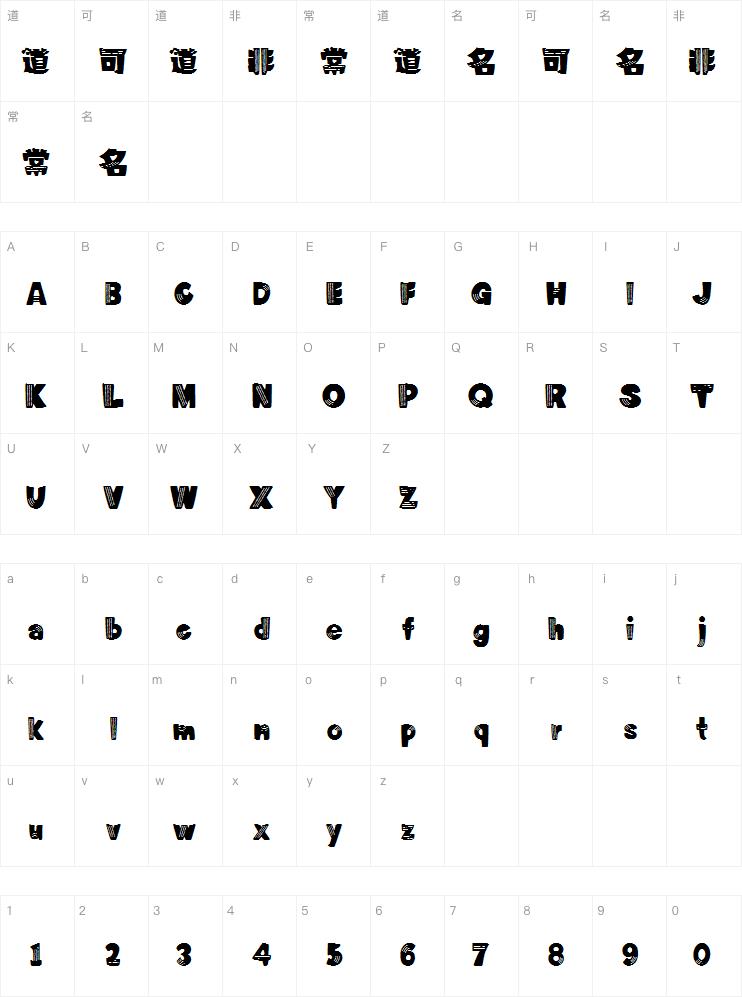
字魂上海交响乐谱体
字魂上海交响乐谱
字魂上海交响乐谱体是字魂为上海交响乐团打造的定制字体。这是一款欢快灵动仿佛可以听见声音的字形,字形笔划圆融可爱,视觉感强烈。笔画当中添加了线状装饰,以体现类似五线谱或是琴弦的效果,部分点笔划以音符替代,很形象地体现了音乐和字体的联动。这款字体适用于母婴、宠物、文创潮玩、包装设计等场景。
字魂上海交响乐谱体